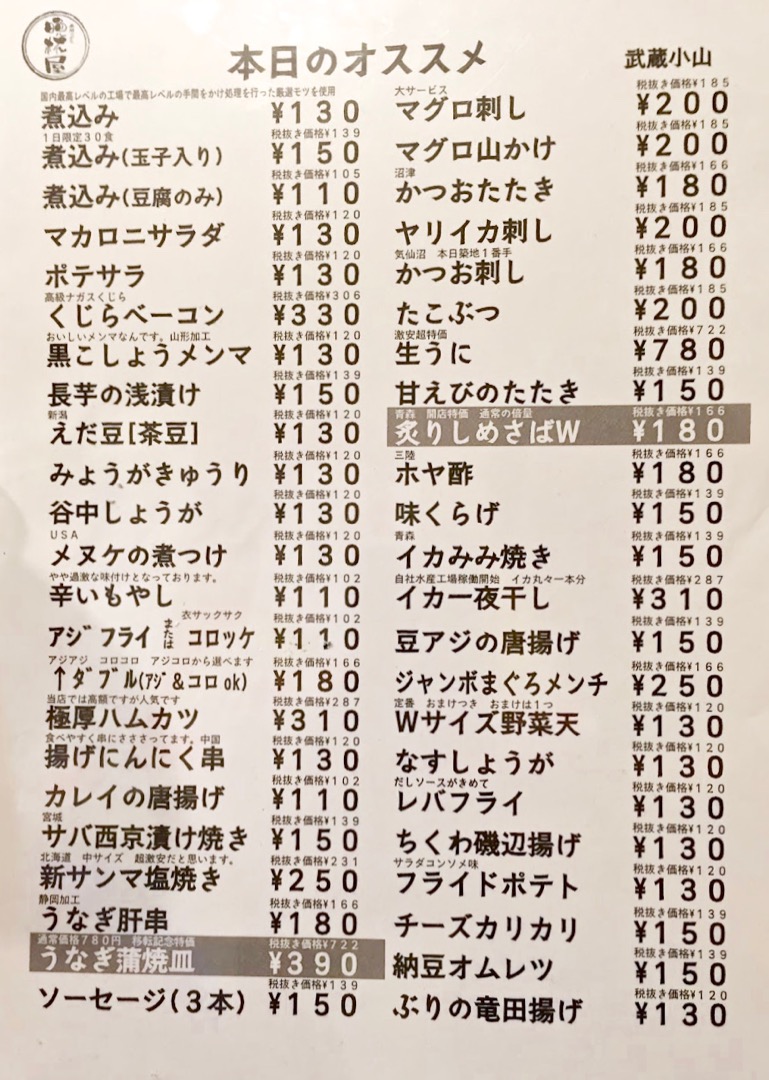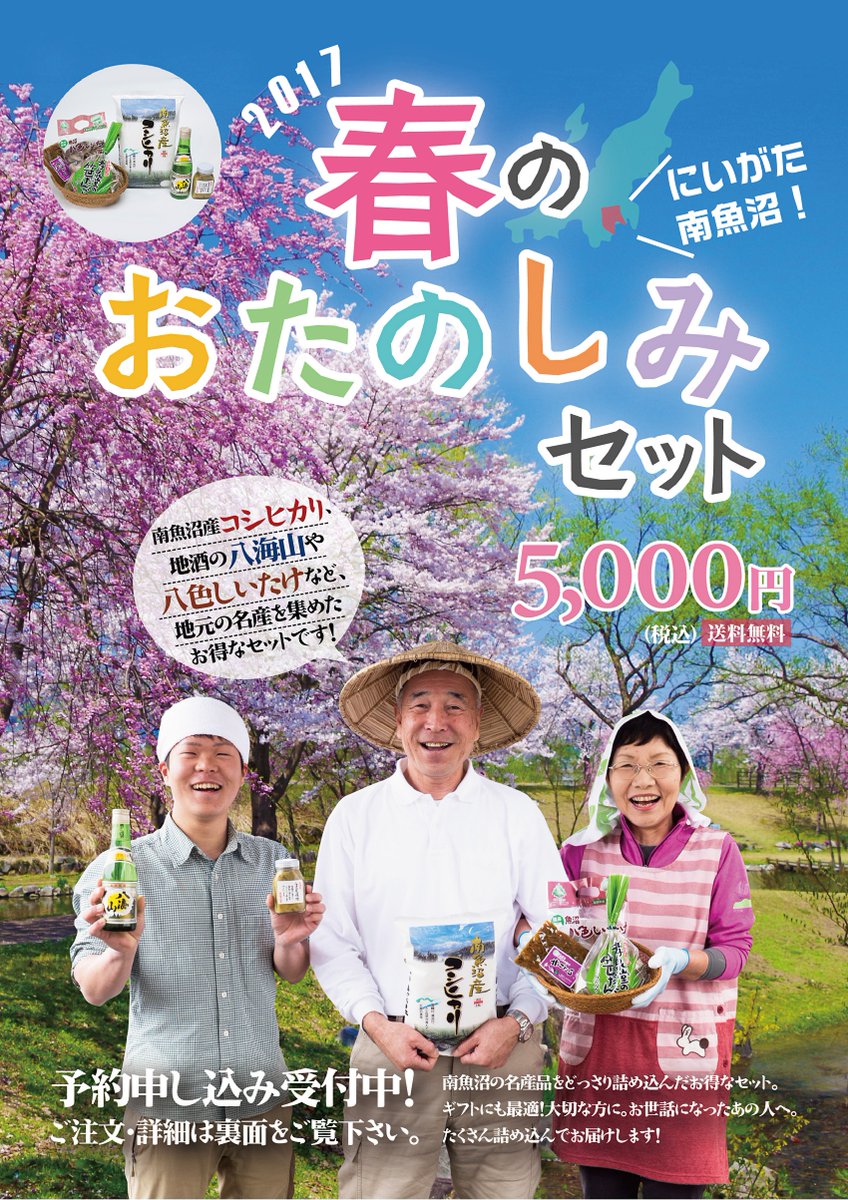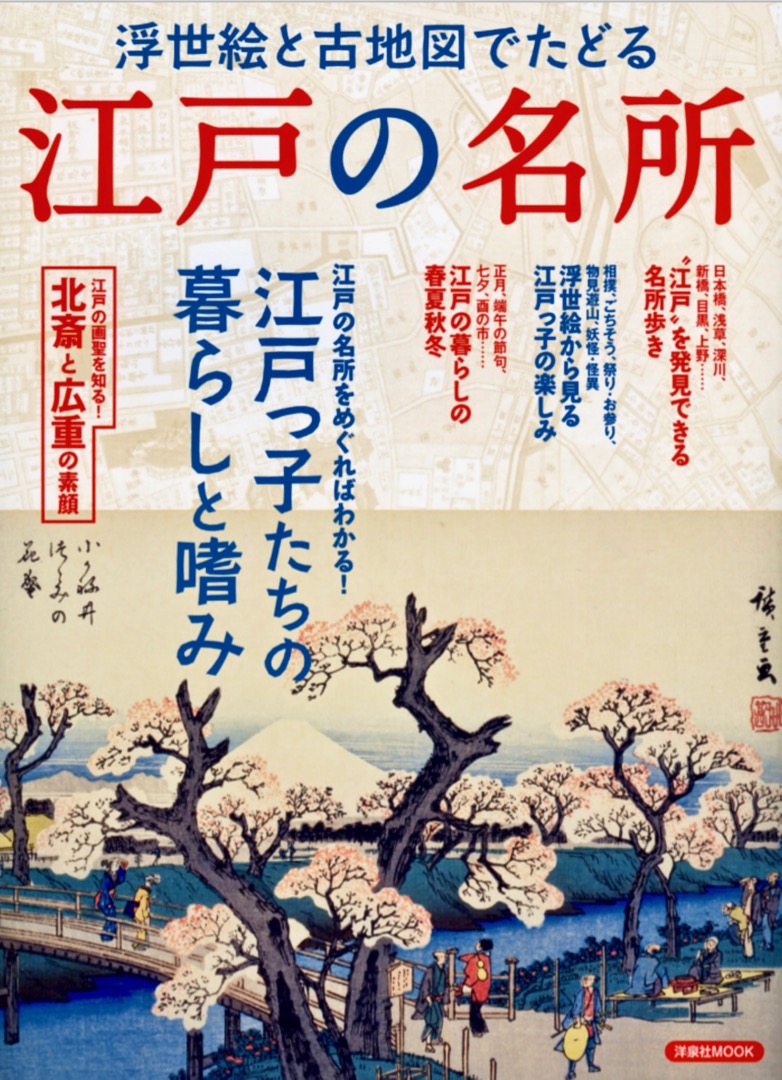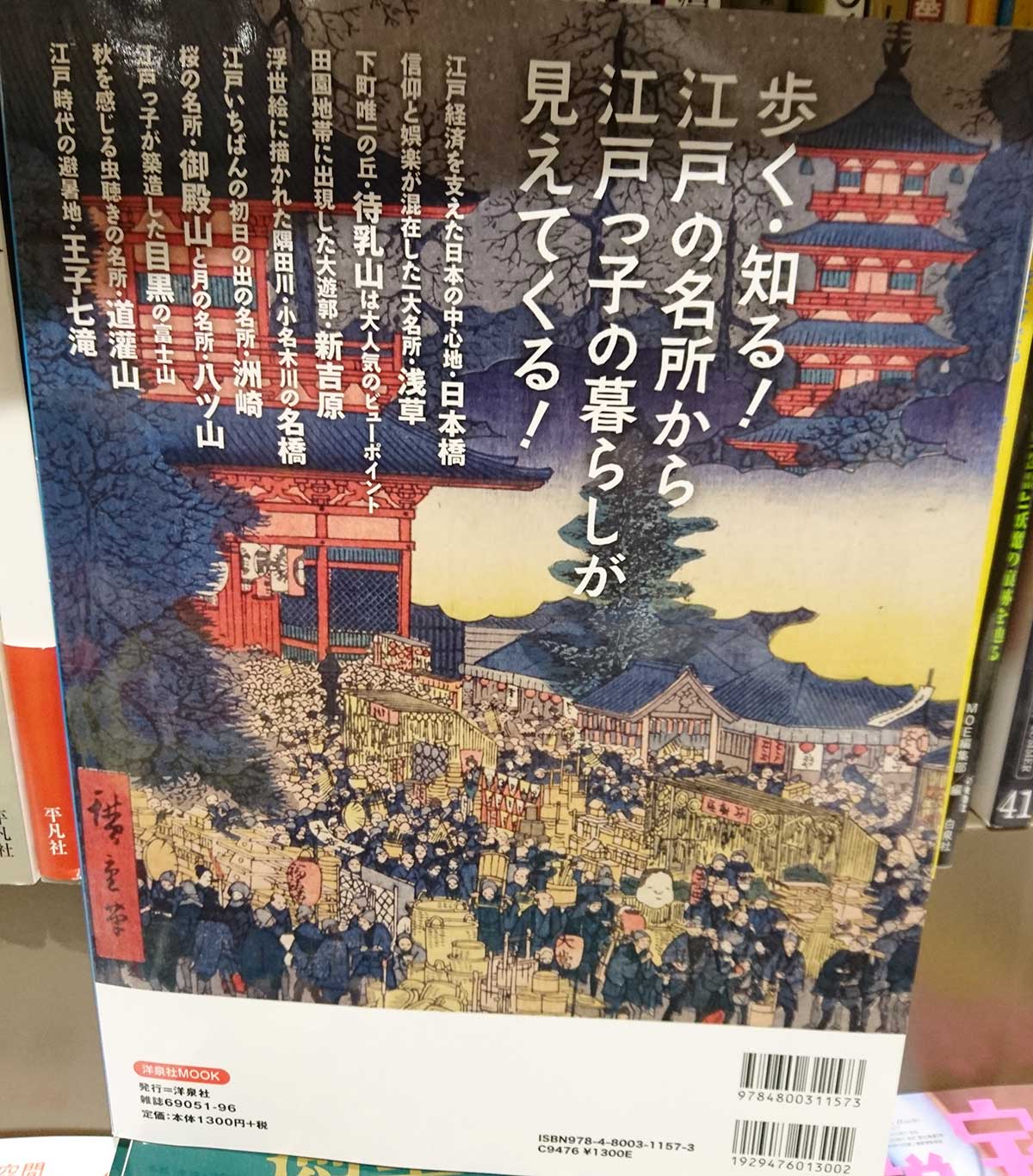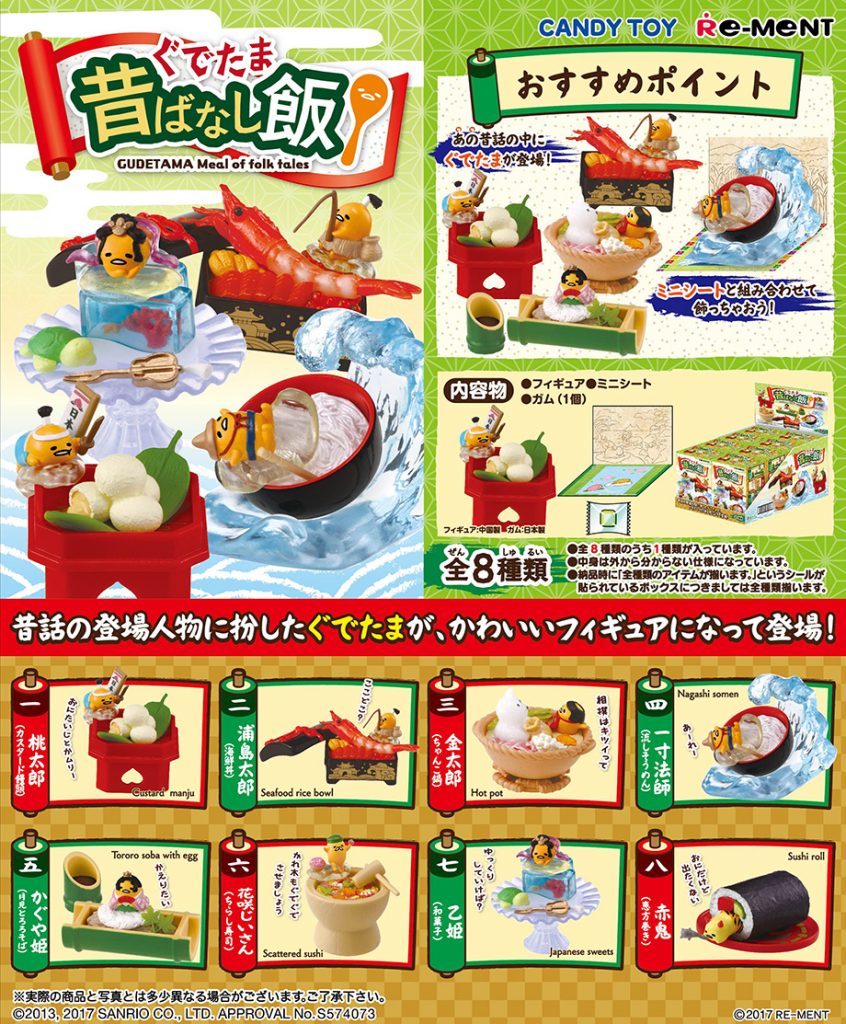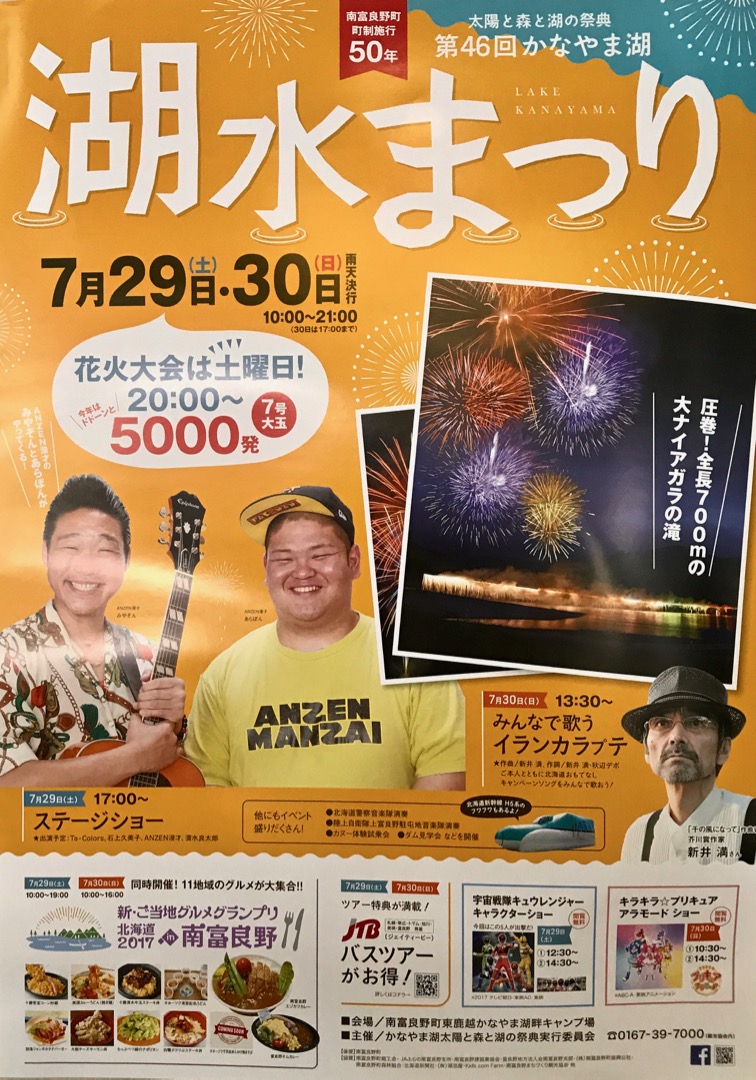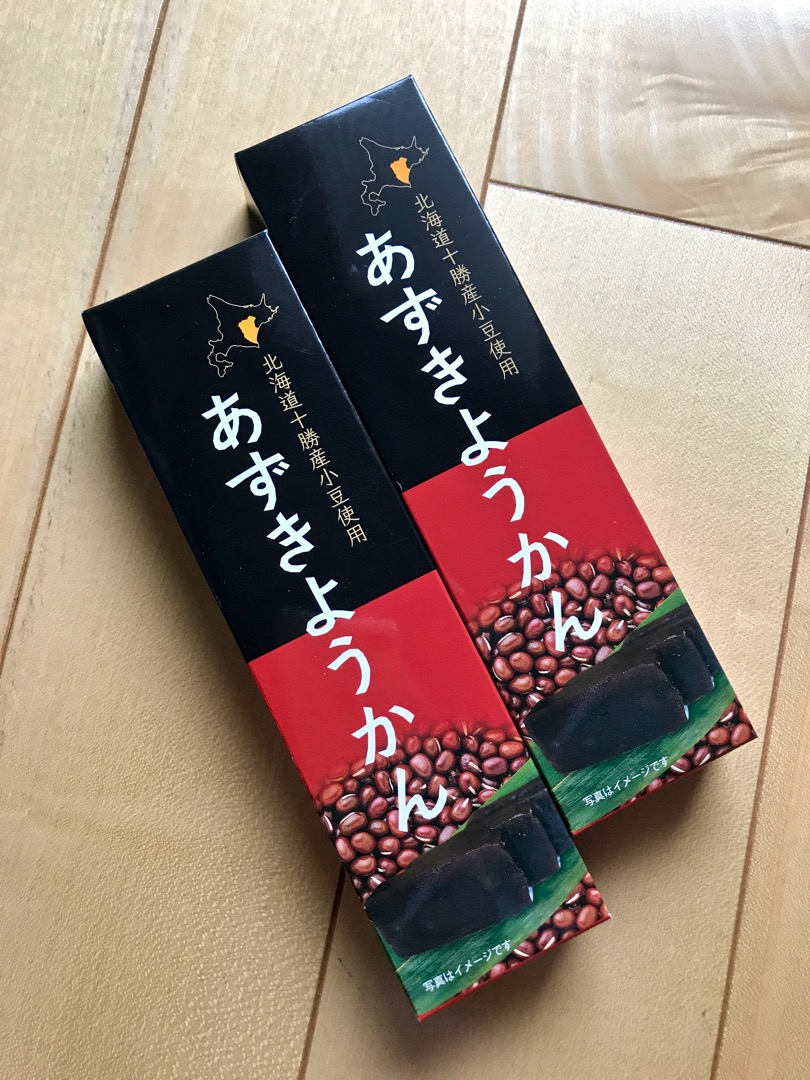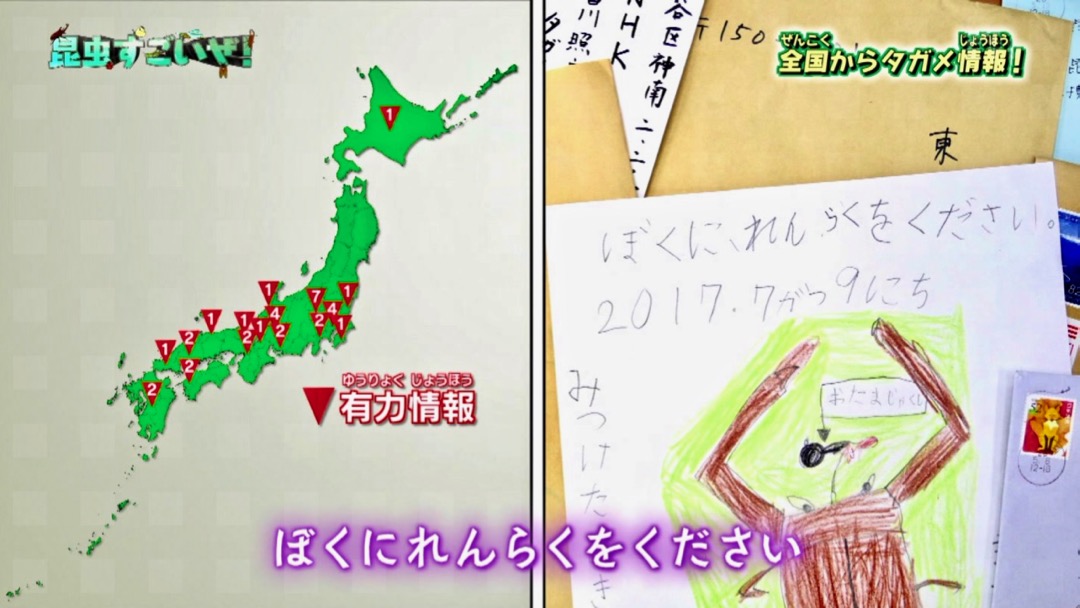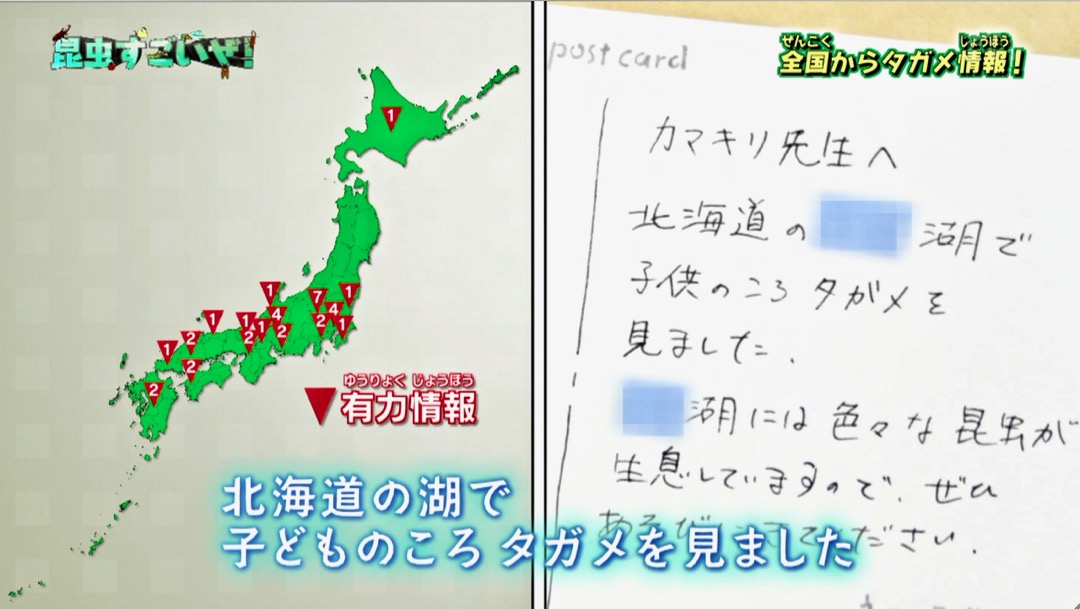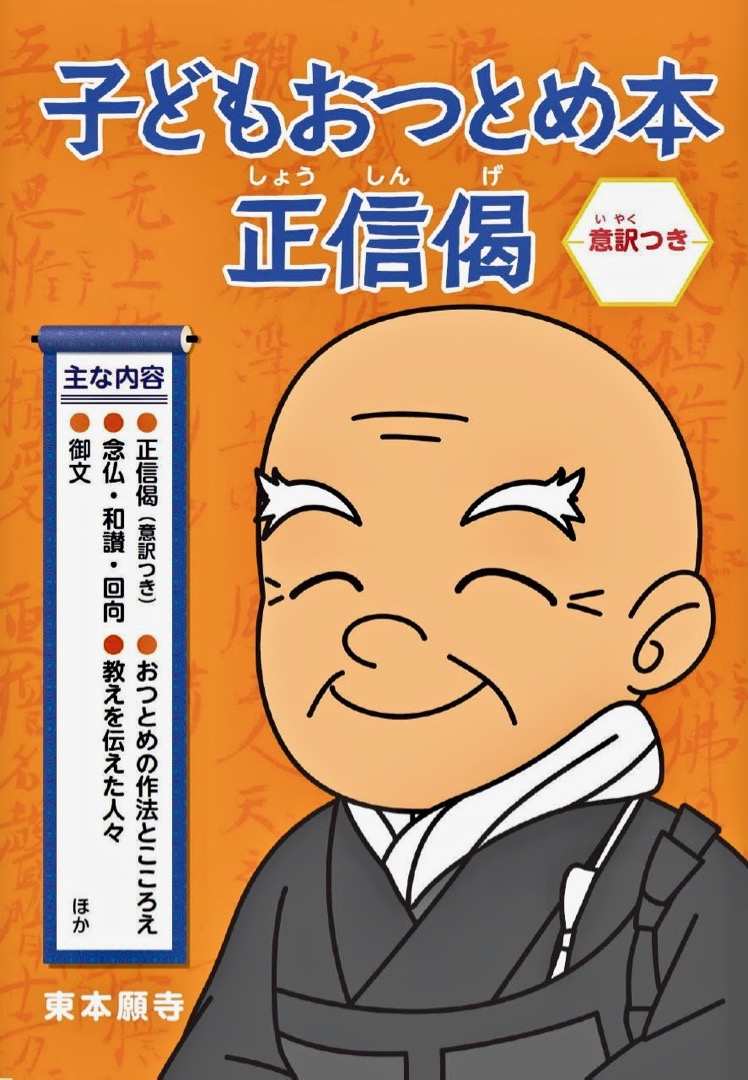
ネコ番組のテロップ さとうゆたか
番組名:岩合光昭の世界ネコ歩き
放送局:NHK BSプレミアム
月に1回の放送らしいです。
これも同番組で使われたものだと思います。
もうひとつ。
夏まつり 大阪のうめ吉
大阪市平野区で、300年以上の歴史をもつ杭全(くまた)神社の、「平野郷夏まつり」のパンフレット(A4判44ページ)で使用されています。
J:COMメルマガ 大阪のうめ吉
今朝届いた、電話、ネットなどで契約しているJ:COMからのメルマガ「J:COMeマガジン」7月号です。
画像ソフトを使用して装飾しているようです。
テレビ番組 さとうゆたか
テレビ東京の「インテリア日和」。
「演歌歌謡通信」見出し 大坂のうめ吉
作っているミニコミ紙「演歌歌謡通信」の見出しです。
「えれがんと」「セプテンバー」も使用しています。
大きく使うと、表情が出てきますね…。
先のに続きもう1件見つけました。同じくよどがわ市民生協のカタログです。 先のよりかなり小さいです。右下がカタログ半分の全面。中央は部分拡大です。
市民生協カタログ 古谷守(大阪のうめ吉)
大阪よどがわ市民生協(パルコープ)のカタログ、新製品特集のページです。
カタログはB4判。大きいので写真はその半分です。
こういう地域性のある印刷物は、なかなか目に出来ませんのでウレシイです。
新聞広告 さとうゆたか
中古着物の販売広告ですね。
TV番組 さとうゆたか
テレビ朝日スーパーJチャンネルの月曜企画。
ついつい当たっちゃう!キャンペーン takumi
Twitterの、gooサンクスチームのアカウント(@goo_thanks)に貼られていたバナーであられフォントが使われていました。
古風なイメージのフォントですが、こういう使い方もアリですね。
どんな場面でも、使い方次第ってことですね。